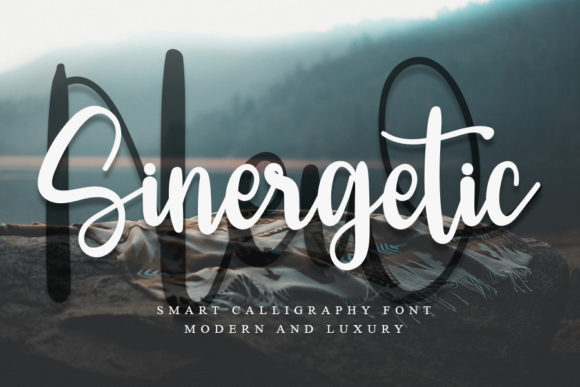
Creativefabrica New Sinergetic Font
[Creativefabrica] New Sinergetic Font
Новый Sinergetic - это романтичный и изысканный шрифт для сценария.
Это лучший выбор для создания привлекательных логотипов, брендинга и кавычек.
Каждая буква имеет уникальный и красивый штрих, который оживит ваш дизайн!